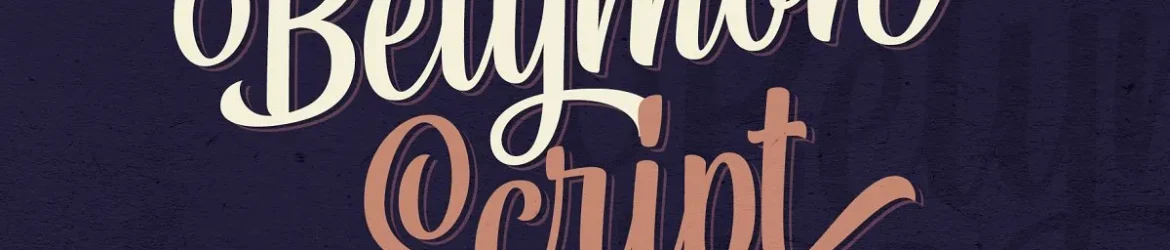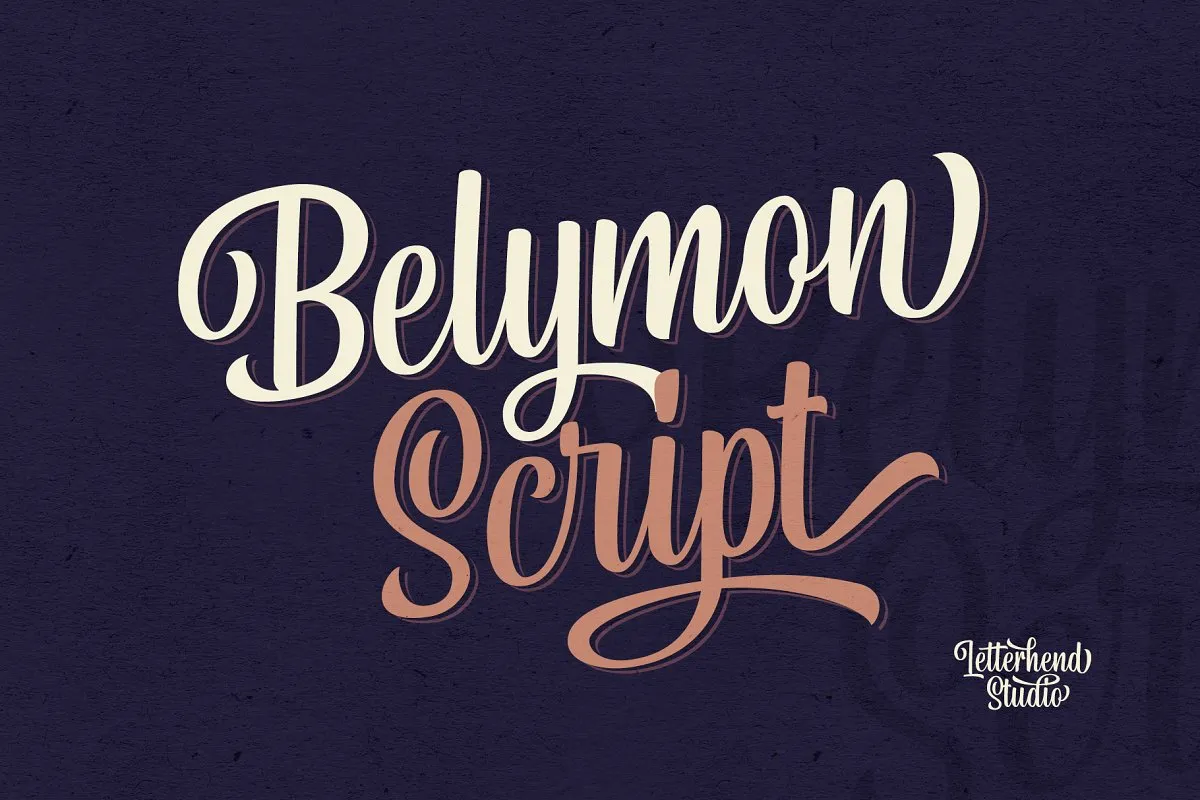
Belymon Script Font – Fonte Grátis
Belymon Script Font
A Belymon Font é uma escolha perfeita para quem está procurando por uma fonte tipográfica com toque giratório e levemente deslumbrante, ideal para logotipos, roupas, convites, marcações, embalagens e propagandas. Desenvolvida pela equipe de designers da 0001themes, essa fonte especializada em scripts é uma criação única que combina um toque clássico com leitura fácil e confortável. A Belymon oferece a conveniência de ser perfeitamente adaptada para diversos usos visuais, tornando-a uma opção ideal para quem busca um estilo único e chamativo. Uma vez instalada em seu sistema de computador, essa fonte é certamente uma excelente adição ao seu arsenal criativo, ajudando você a dar vida aos seus projetos, seja na web ou nos documentos impressos.